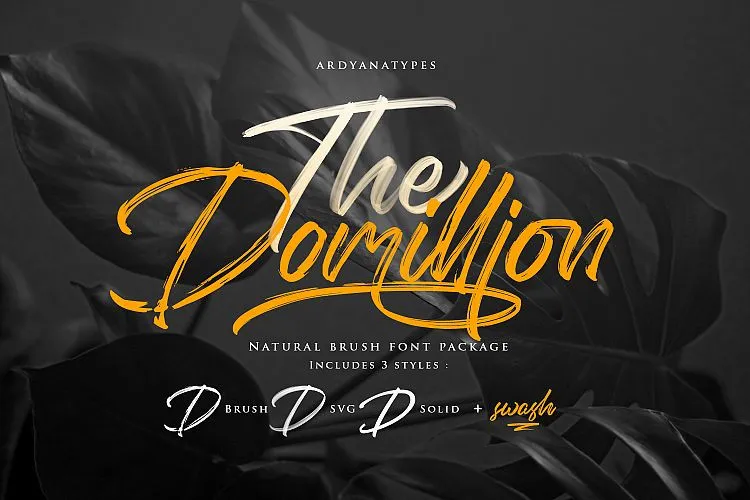
Sintam-se à vontade para explorar a The Domillion Font neste download especial. Esta elegante fonte script foi cuidadosamente projetada por Ardyanatypes com texturas altamente definidas, criando um estilo único que se destaca no meio das opções disponíveis. A The Domillion é feita de traços naturais e raspaduras feitos à mão, perfeitos para adornar seus trabalhos. Seu design apresenta 3 variações dos acentos: Brush, SVG e Clean. Cada uma dessas variadas formas traz seu próprio charme ao conjunto de recursos da fonte. Com certeza, ela se tornará um aliado indispensável em qualquer projeto criativo que você estiver desenvolvendo. Experimente agora e enriqueça suas obras com a The Domillion Font.